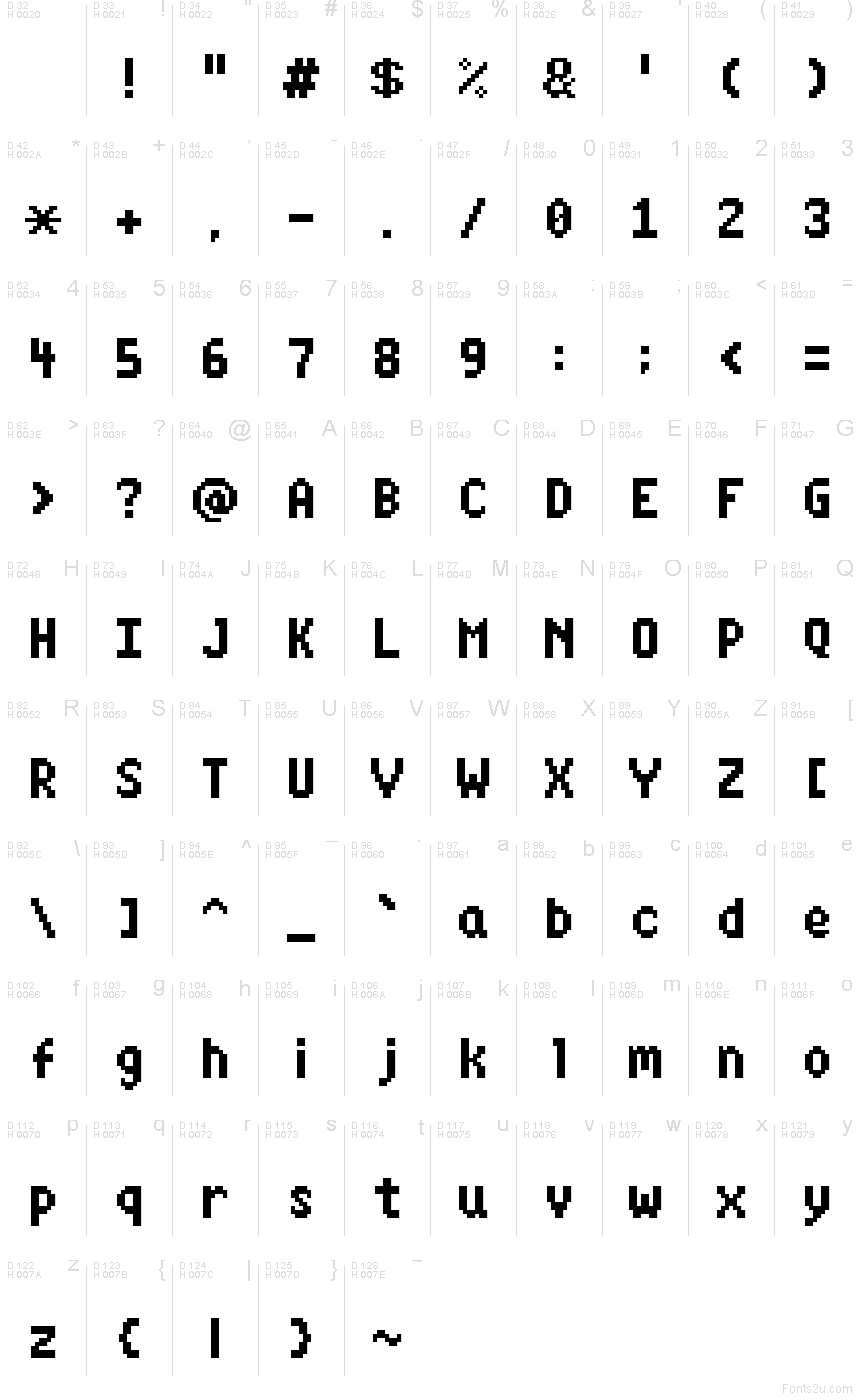
SilverXSPremiumC
SilverXSPremiumC od TLF je bezplatné pixelové písmo typu display tvořené masivními tahy s ostrými hranami. Jeho odstupňované diagonály a zkosené rohy připomínají rané arkádové nápisy, přičemž těsné spoje dodávají tvarům hustý, mechanický vzhled. Opakující se pravé úhly udržují design čistý a záměrně nízkorozlišovací.
Herní rozhraní i vizuály elektronické hudby se hodí k jeho obrazovkové konstrukci a písmo může také propůjčit technologickému merchandise přesvědčivé retro-digitální razítko. Nejlépe vyniká na úvodních obrazovkách arkádových her.